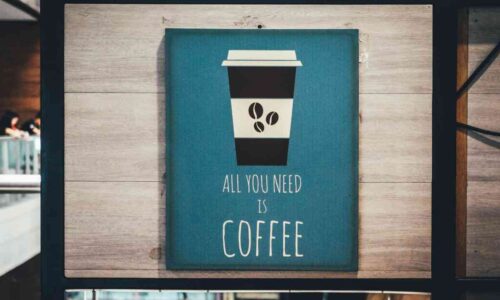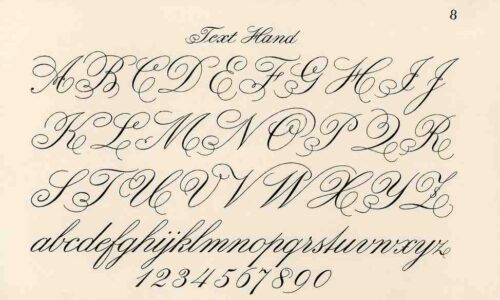
Lima kategori utama dalam klasifikasi font: serif, sans serif, script, display, dan monospace, masing-masing dengan karakter visual yang berbeda.
Jenis-jenis font dan contohnya adalah materi dasar yang wajib dipahami oleh siapa pun yang menggarap konten visual, mulai dari pemilik bisnis kecil sampai desainer agency. Pemilihan font yang tepat bukan sekadar urusan estetika, melainkan strategi komunikasi yang memengaruhi cara audiens mengingat brand. Menurut riset Linearity (2024), konsistensi penggunaan font tertentu dapat meningkatkan pengenalan brand hingga 80%, dan survei WifiTalents (2026) bahkan menyebut 90% kesan pertama terhadap sebuah brand terkait langsung dengan tipografi yang dipakai.
Yang menarik, dari pengalaman tim Creativism mendampingi belasan klien lintas niche, kesalahan terbesar yang sering kami temui justru bukan soal kurang pilihan font. Sebaliknya, banyak brand pakai 5 sampai 7 jenis font yang saling tabrak di materi mereka, padahal patokan studi tipografi terbaru (JUKIM, 2025) menyarankan maksimal 2 typeface dalam satu desain. Artikel ini akan mengupas tuntas klasifikasi font, contoh konkret, dan cara memilihnya sesuai kebutuhan, supaya tidak terjebak tren yang justru bikin desain terlihat amatir.
ToggleSebelum masuk ke klasifikasi, ada satu kerancuan istilah yang sering bikin diskusi desain melebar. Banyak orang menyamakan font dengan tipografi, padahal dua hal ini berbeda. Font adalah satu set karakter, huruf, angka, dan simbol dalam satu gaya visual tertentu, misalnya Times New Roman ukuran 12 reguler. Sedangkan tipografi adalah seni dan teknik menyusun huruf agar pesan tersampaikan dengan jelas dan estetis, termasuk pemilihan jenis huruf, jarak antar huruf (kerning), spasi baris (leading), dan hierarki teks.
Analogi sederhananya, kalau tipografi adalah masakan, font itu bumbunya. Anda bisa punya bumbu terbaik di dunia, tapi kalau cara memasaknya keliru, hasilnya tetap tidak enak. Sebaliknya, koki andal bisa menyajikan hidangan istimewa dengan bumbu sederhana sekalipun. Inilah kenapa banyak desainer pemula berpikir kualitas desain hanya soal pakai font mahal, padahal kompetensi tipografi (penyusunan, pasangan font, ritme visual) jauh lebih penting dari nama font itu sendiri.
Dari sisi praktis, font adalah file digital yang Anda install di komputer atau pakai di aplikasi seperti Canva, Photoshop, dan Figma. Saat ini, lebih dari 1.500 font open source tersedia di Google Fonts dan sekitar 25.000 font di Adobe Fonts. Banyaknya pilihan ini justru sering bikin pemula bingung memilih. Solusinya bukan menambah pilihan, tapi memahami klasifikasi dulu agar tahu kapan font tertentu cocok dipakai.
Detail kait kecil di ujung huruf adalah pembeda utama antara font serif (kiri) dan sans serif (kanan).
Font serif dikenal lewat detail kait kecil atau guratan di ujung setiap huruf. Kait ini disebut “serif” dan merupakan warisan dari teknik pemahatan huruf di batu pada era Romawi kuno. Karena bentuknya yang mengarahkan mata dengan halus, font serif sangat nyaman dibaca untuk teks panjang. Tidak heran kalau koran, buku, dan jurnal akademik masih dominan pakai jenis ini. Data WifiTalents (2026) mencatat sekitar 70% surat kabar cetak dan 80% jurnal akademik tetap setia menggunakan font serif untuk badan teks utama.
Secara visual, serif memunculkan kesan stabil, kredibel, dan punya warisan sejarah. Inilah alasan logo Time Magazine, The New York Times, dan brand pendidikan tradisional seperti Harvard dan Cambridge memilih font serif sebagai identitas. Tapi jujur saja, ada salah kaprah yang sering kami temui di klien: serif tidak selalu berarti kuno atau formal kaku. Font serif modern seperti Playfair Display atau Lora justru sering kami rekomendasikan untuk brand fashion dan kuliner premium yang ingin terlihat berkelas tanpa kehilangan sisi kontemporer.
Pro Tip: Kapan Pakai Serif
Pakai serif untuk badan teks panjang, dokumen formal, materi cetak, dan brand yang ingin menonjolkan tradisi atau kredibilitas (perusahaan hukum, lembaga keuangan, penerbit). Hindari untuk badan teks di layar ukuran kecil karena kait halusnya bisa terlihat berantakan di pixel rendah.
Contoh font serif populer: Times New Roman, Georgia, Garamond, Playfair Display, Lora, Merriweather, EB Garamond, Cormorant, dan Crimson Text.
Kata “sans” dalam bahasa Prancis berarti “tanpa”. Jadi sans serif berarti font tanpa kait di ujung huruf. Karakteristiknya bersih, geometris, dan minimalis, menjadikannya pilihan utama untuk media digital. Layar komputer, smartphone, dan tablet menampilkan sans serif jauh lebih tajam dibanding serif, terutama di ukuran kecil. WifiTalents (2026) mencatat sekitar 72% body text di website modern menggunakan font sans serif, dan 75% iklan digital memilih kategori ini demi keterbacaan.
Nah, ini yang sering jadi pertanyaan klien: kenapa hampir semua brand teknologi global pakai sans serif? Google pakai Roboto, Apple pakai SF Pro, Facebook pakai Helvetica, Netflix pakai Netflix Sans yang custom. Jawabannya kombinasi: sans serif terbaca jelas di semua ukuran layar, terlihat modern tanpa beban historis, dan netral secara budaya sehingga gampang diterima audiens global. Menurut survei Monotype Global Font Use (2024), sans serif jadi pilihan top desainer karena alasan readability dan accessibility yang dipikirkan 76% responden.